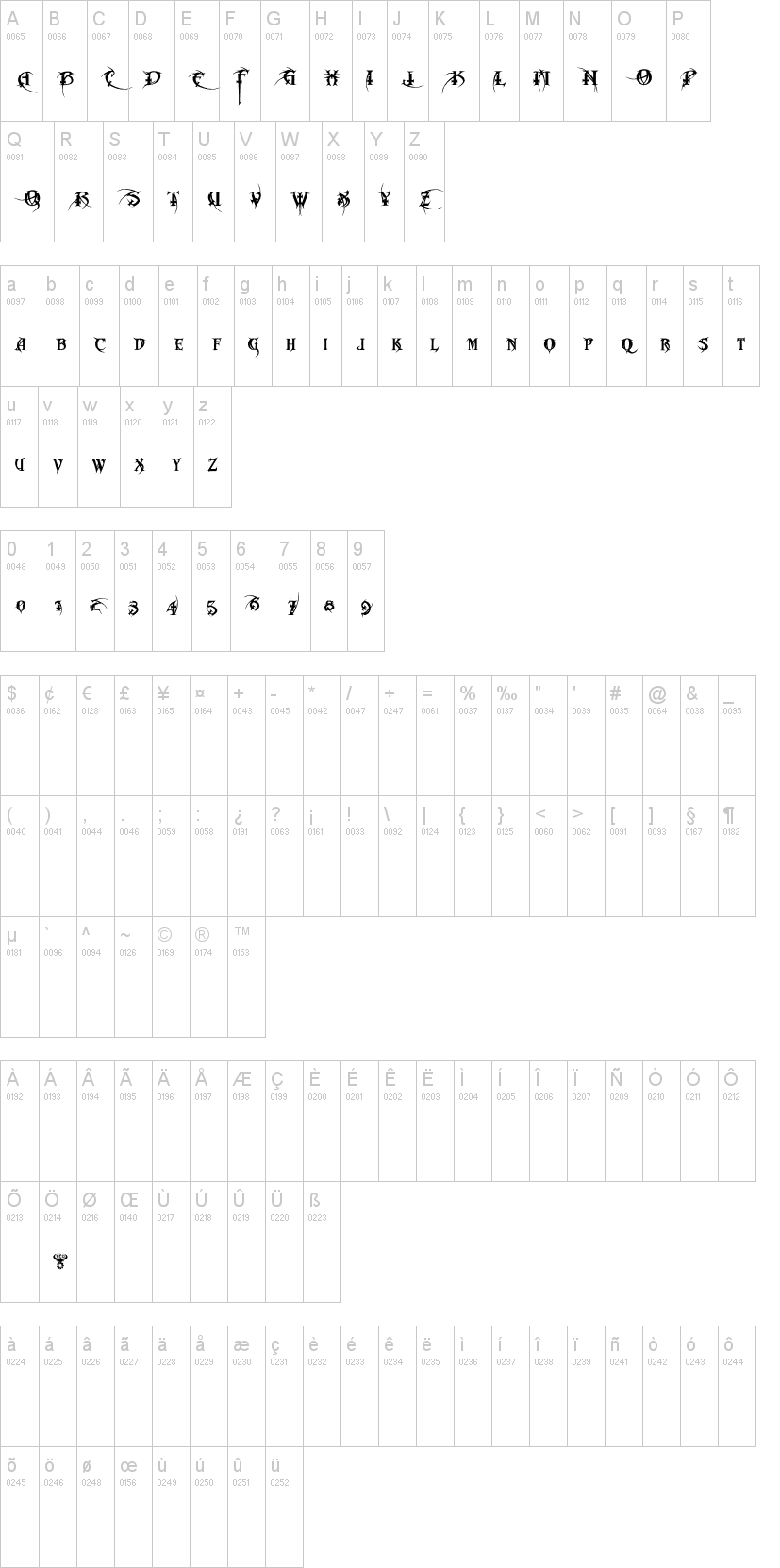
Metal Macabre
Metal Macabre字体是一款极具特色的炼金术风格字体,它带有强烈的古典元素,充满了邪恶的气息。字体的线条粗细不一,笔画流畅,有着独特的质感,体现出极强的空间感和视觉冲击力。它可以用于各种封面、标题、图标、海报等设计中,为作品增添一份恐怖又迷人的气息。
Metal Macabre是一款非常不错的手写艺术字体,具有很好的视觉感,适合于文化类的宣传设计、商业类品牌的广告和产品包装设计以及个性化文字排版等较多场景。
Metal  Macabre字符映射图